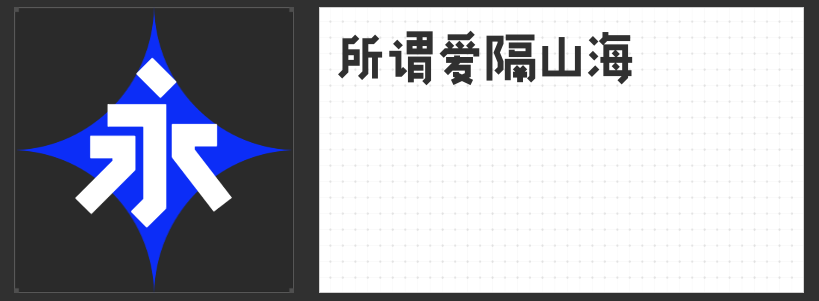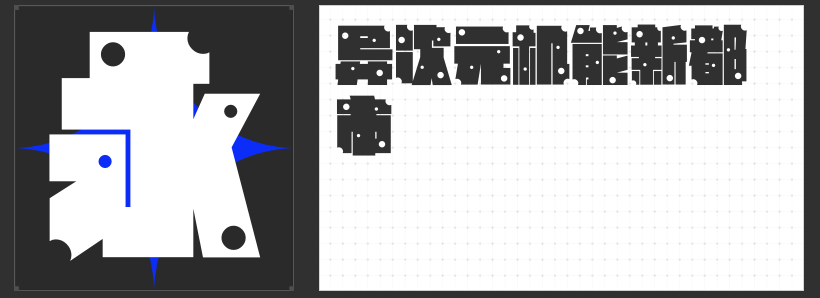
游戏视觉革命:四款创意字体重塑游戏美学新境界
在游戏设计的宇宙中,字体不仅是信息的载体,更是氛围营造的关键元素。一款恰到好处的字体,能够瞬间点燃玩家的情绪,引领他们穿越至奇幻的游戏世界。以下四款专为游戏设计打造的创意字体,以其独特魅力,为游戏视觉体验注入无限活力。
一、励字雪花特效简
这款字体以其饱满方正的字型与夸张的直线笔画,奠定了坚实的视觉基础。巧妙融入的大小不一圆形元素,如同冬日飘落的雪花,轻盈而富有层次。对角线的圆角处理与内部雪花圆点的对角摆放,不仅增强了字体的雪花感,更在保留文字识别性的同时,赋予其极强的视觉表现力,仿佛能将玩家带入一个银装素裹的奇幻世界。
二、励字超级勇士简 中粗
以严谨庄重的字型为基底,笔画间直线与弧线的简洁结合,展现出一种不言而喻的力量感。起、收笔的斜切手法与转折处的圆弧处理,既保留了字体的硬朗,又赋予了其流畅的美感,如同勇士的铠甲,既坚固又灵活,为游戏中的英雄角色量身打造。
三、励字铁拳简 超级黑
这款创意黑体字,以其粗壮的笔画与宽大的字面,构建出饱满的块面感。折角的圆润设计,在视觉上形成强烈的冲击,犹如铁拳出击,势不可挡。它适合用于强调力量与决心的游戏场景,让玩家在第一时间感受到游戏的震撼与激情。
四、励字趣黑简繁
以趣味性为核心,这款字体在部分笔画上进行了别出心裁的断开设计,使得字体更加图形化,富有创意。有棱有角的折起处理,搭配大小错落有致的字体布局与恰当的间距,营造出一种可爱、活泼的氛围,为轻松愉快的游戏体验增添一抹亮色。